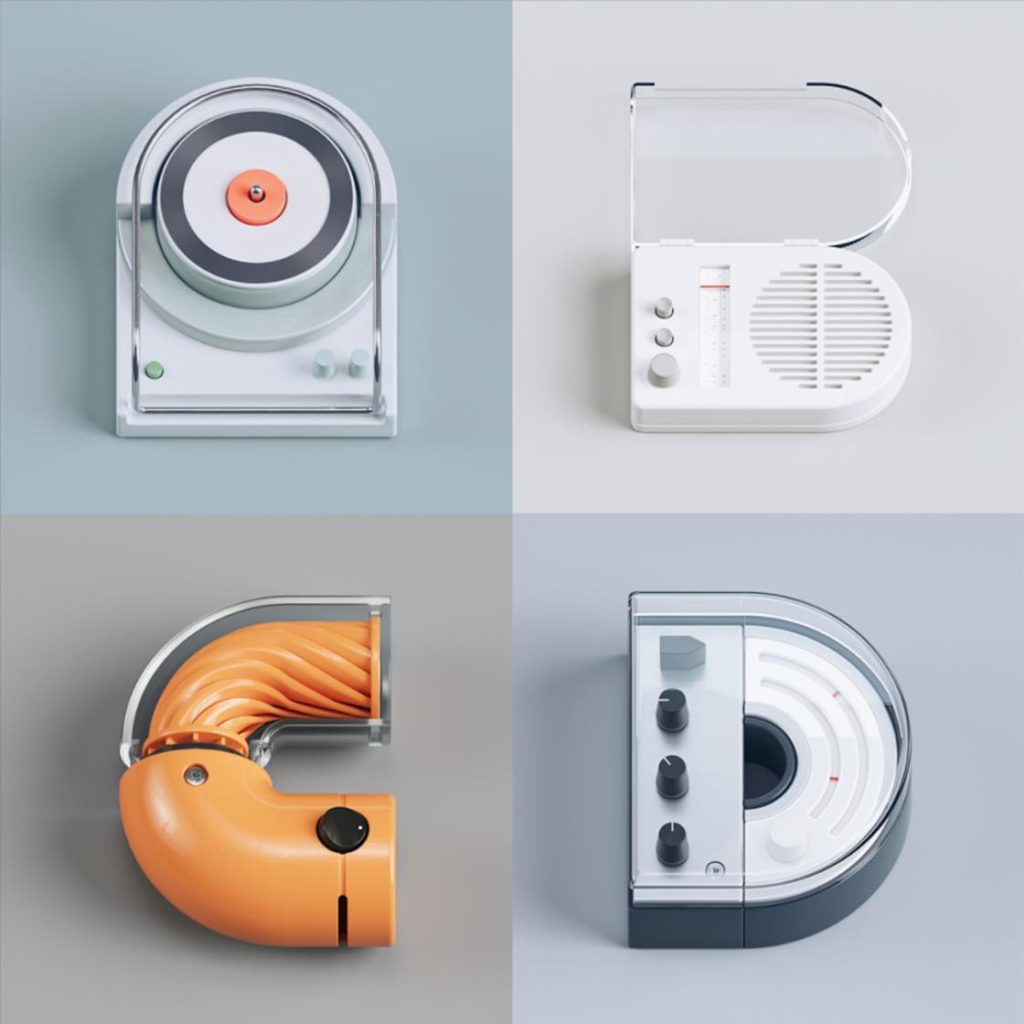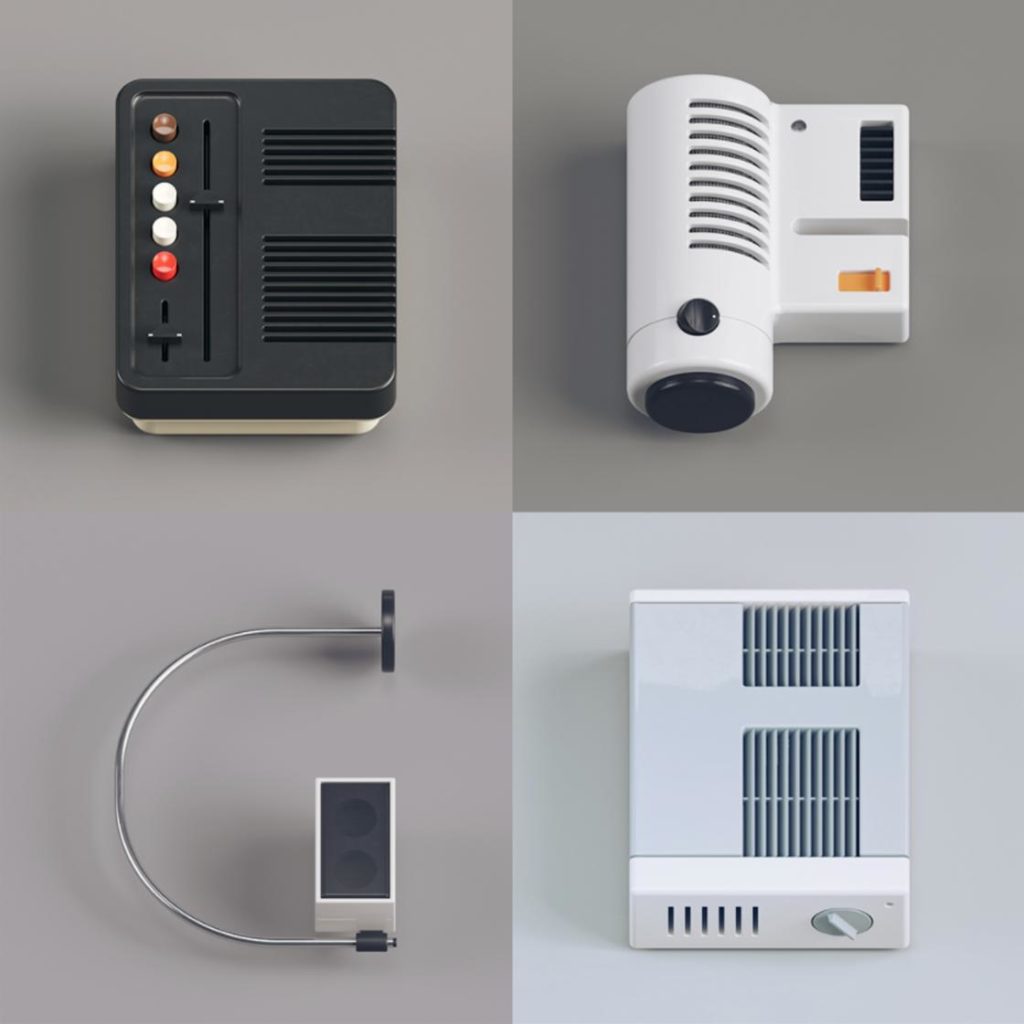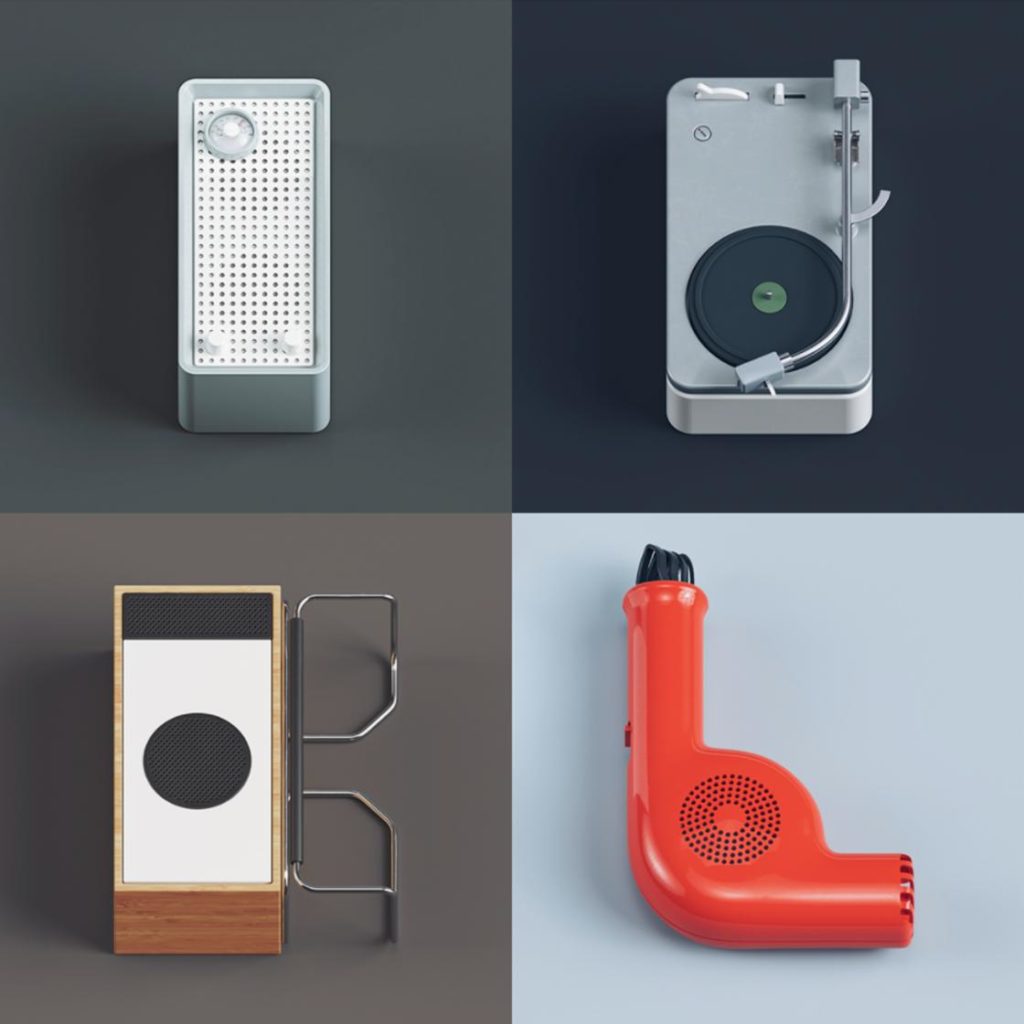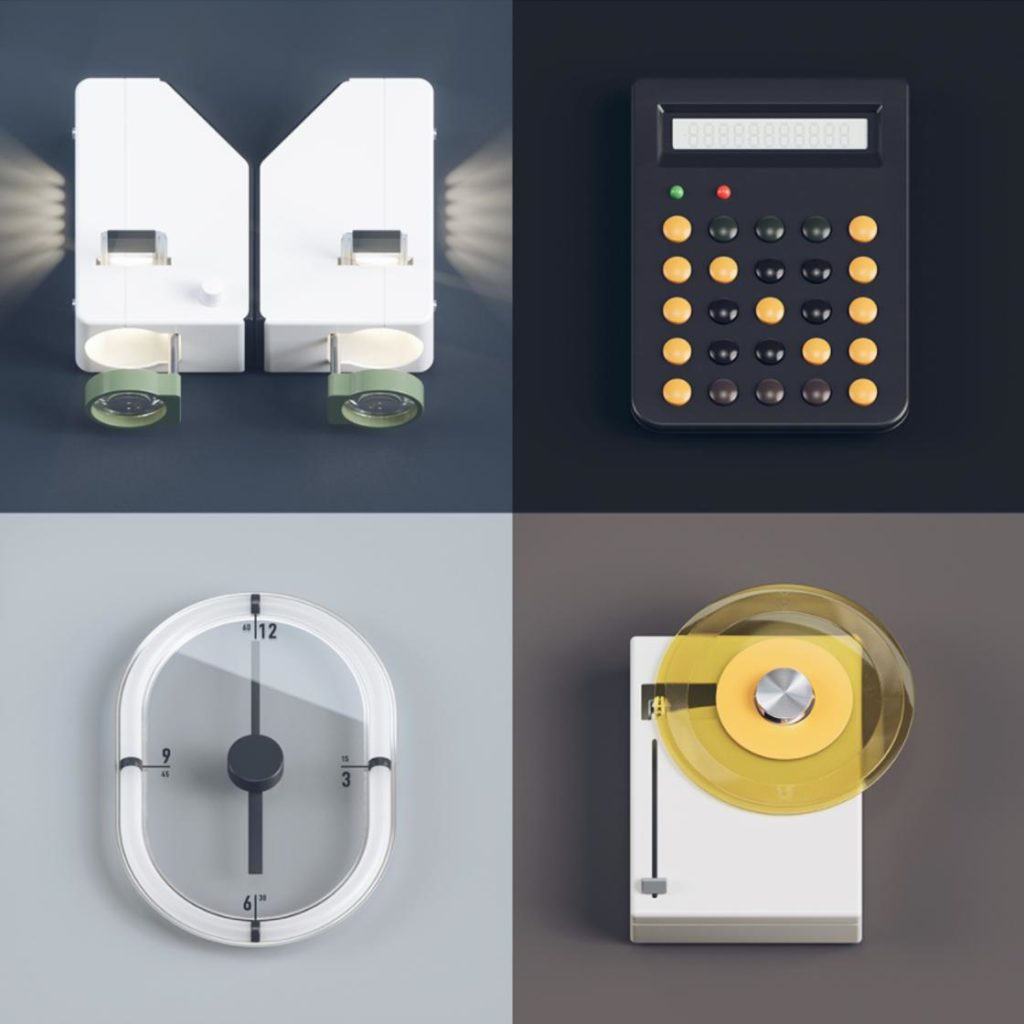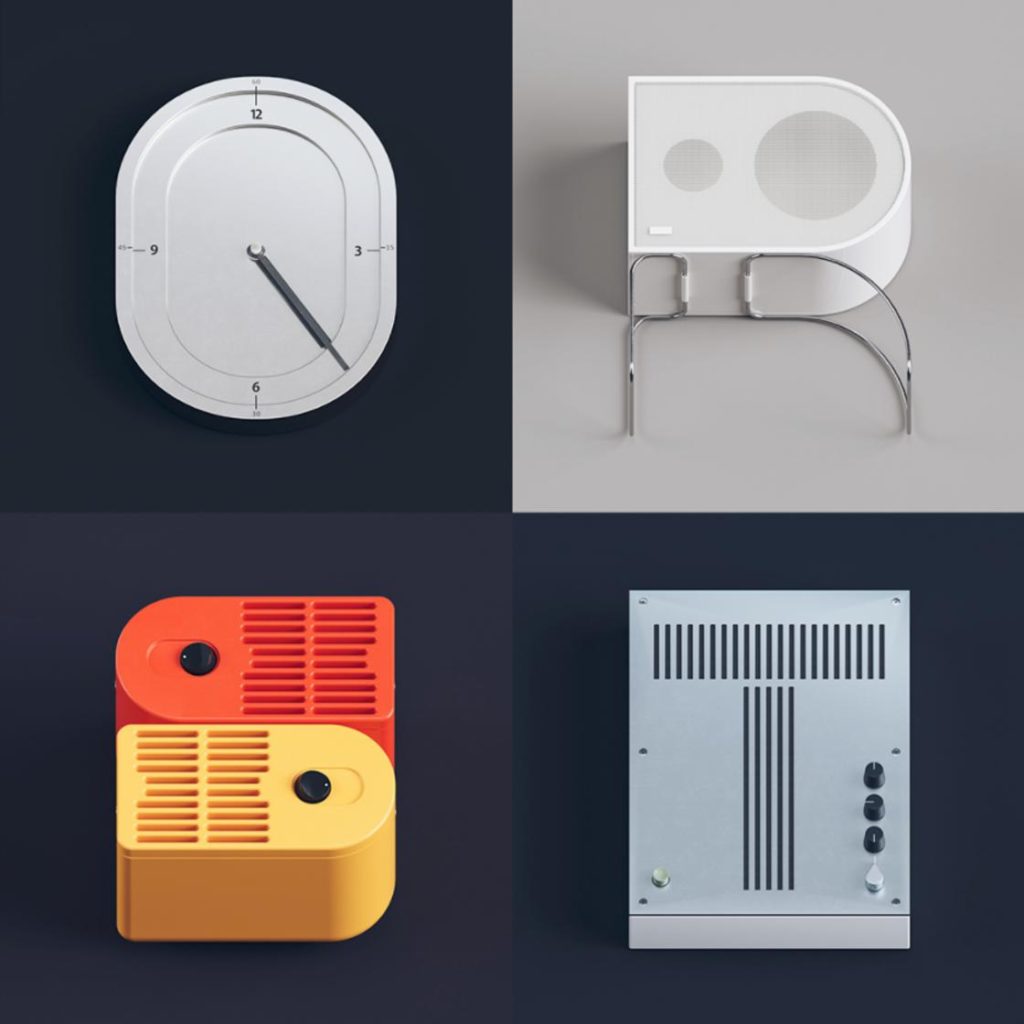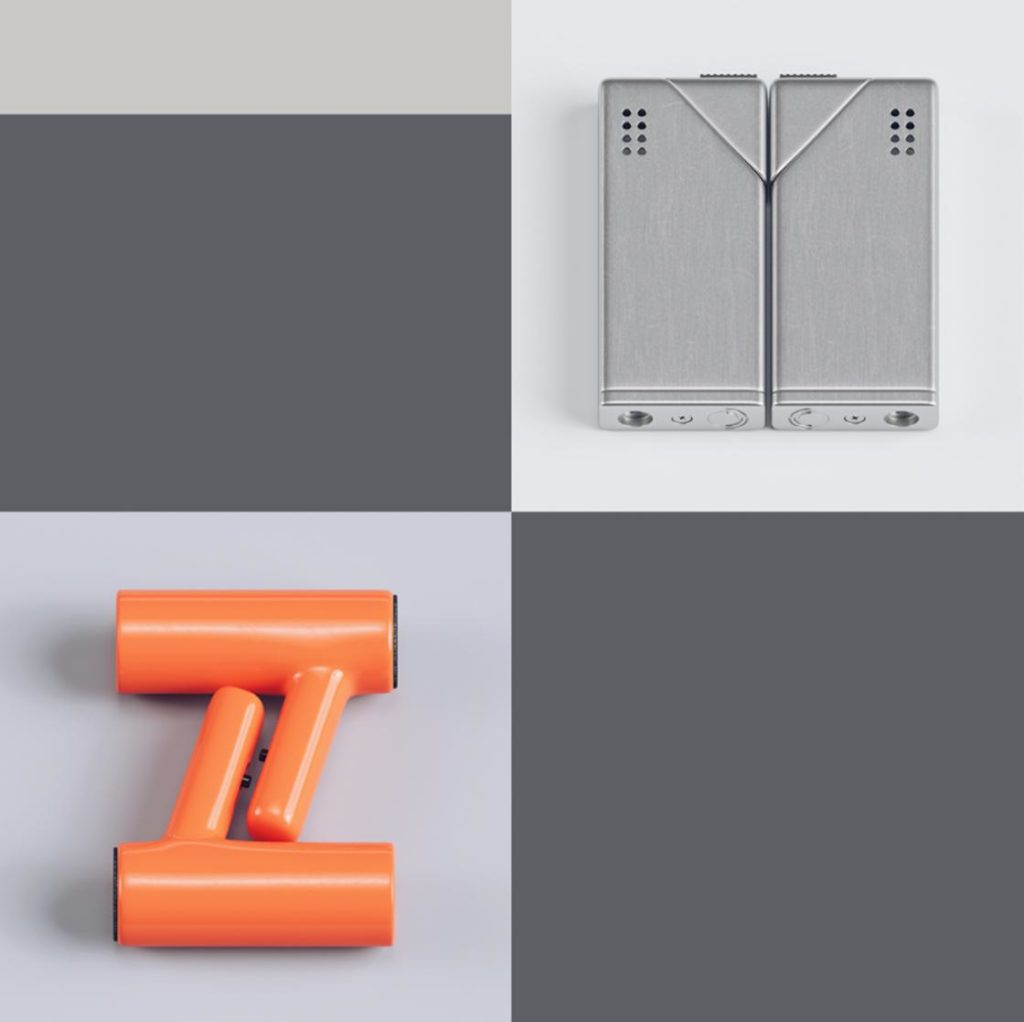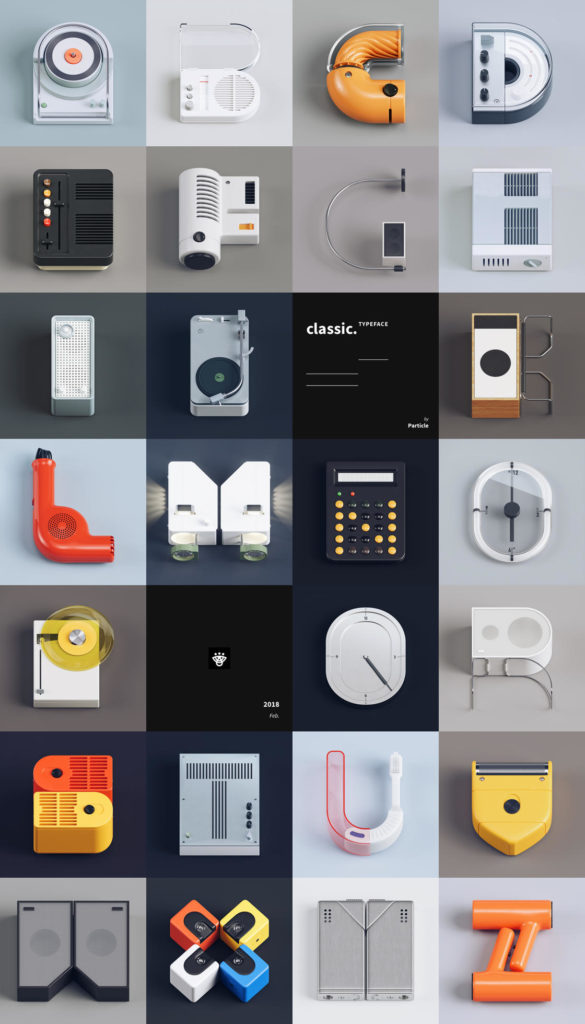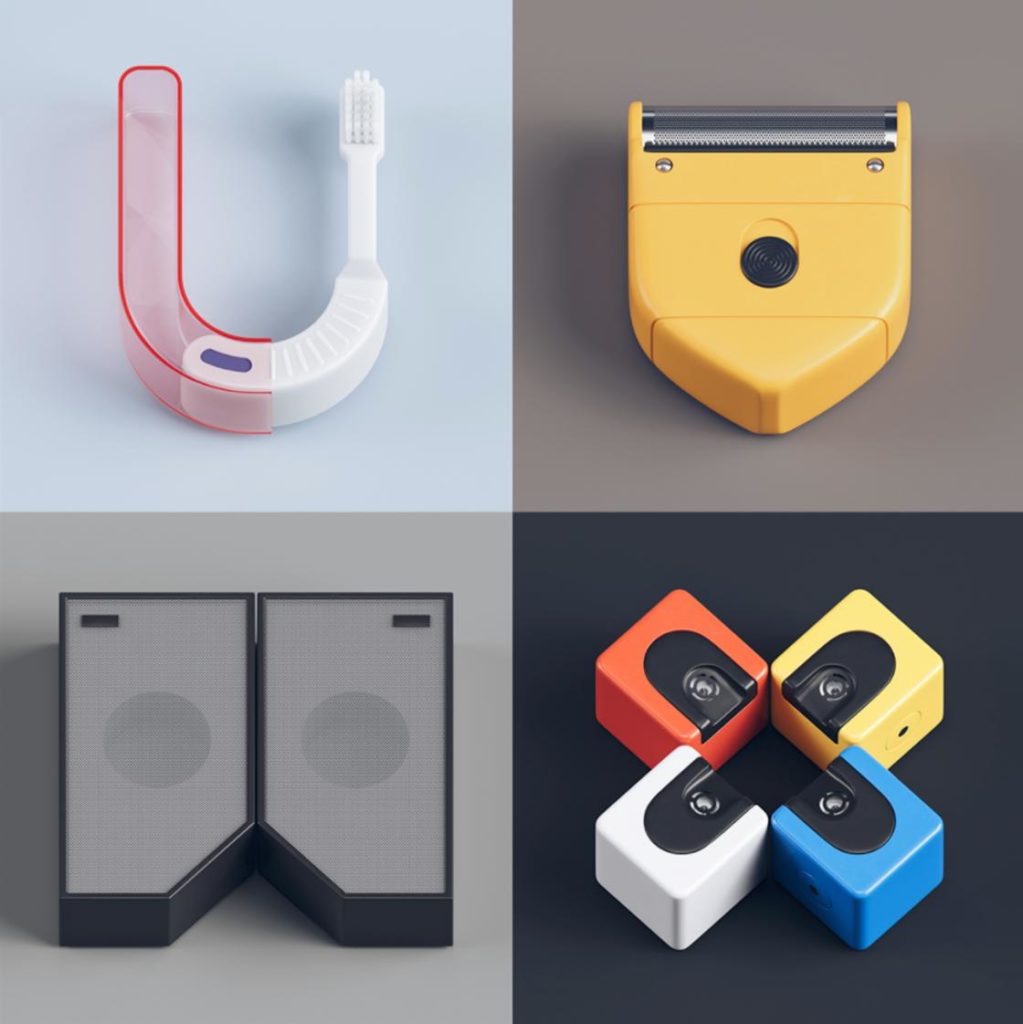
Quando il designer cinese Gao Yang si divertito a rendere omaggio al design retro-futuristico di Dieter Rams direttore del dipartimento di design dell’azienda tedesca Braun e all’estetica dei gadget degli anni ’70 inventandosi e creando un font tipografico in 3D dal titolo Classic Typeface. Un bel progetto che trasforma giradischi, asciugacapelli, stereo o rasoio elettrico in lettere dell’alfabeto. Puoi seguire il lavoro di Goa Yang sul suo portfolio Behance, e ti consiglio anche Electronic Font, in omaggio ai gadget cult dei vecchi tempi.
Classic Typeface – Omaggio Tipografico al design retro-futuristico di Dieter Rams